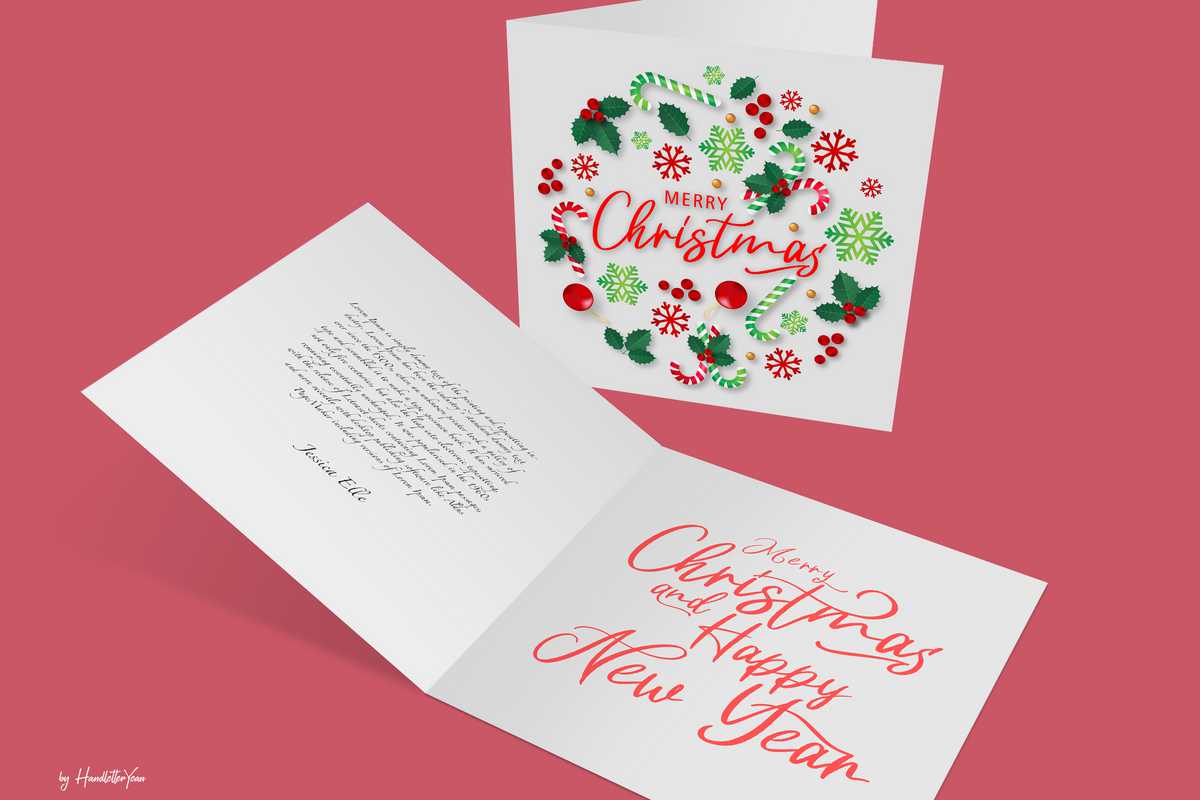
所有活动的冬天对我们来说都是特别有意义的。哈兰岛重新定义了你的假期,让它变得更有意义。哈兰岛的特色包括插页、标题、花饰和衬裙,这将使你的理想变得更加美丽。这是你的工艺品、书籍、封面、名片、海报、标志、杂志、封面、横幅、T恤衫、,即使是大规模的艺术活动。所有活动的冬天对我们来说都是特别有意义的。哈莱尼会让你的假期变得更有意义。哈莱尼的特色包括插页、标题、涂鸦和内衣,这会让你的理想变得更加叛逆。这让你的工艺品、书籍、封面、名片、海报、标志、杂志、封面、横幅、T恤衫、,Orevenartworkinalargescale。